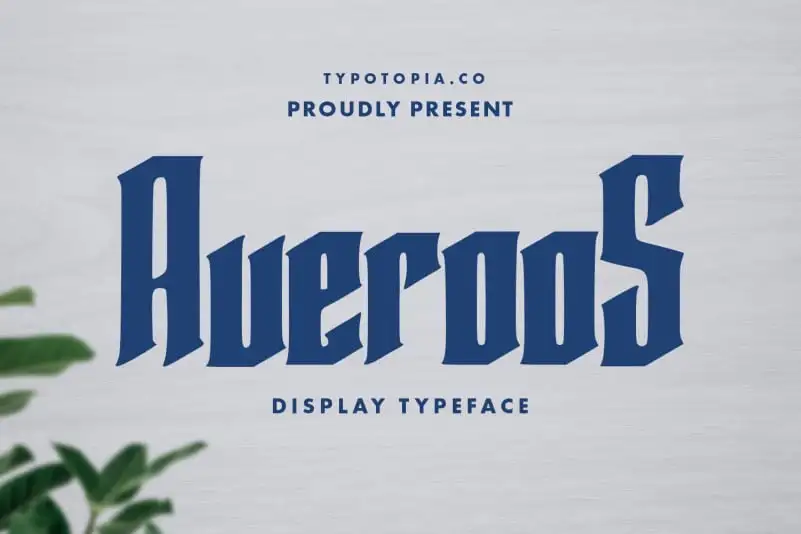
Averoos Display Font – Download Grátis
Introduzimos a Averoos Display Font – uma tipografia de destaque com estilo Semi-Vintage. Este tipo de letra foi projetada para ser aplicada especificamente em logotipos, posters, material de embalagem, revistas, menus, livros, convites, cartas de cumprimento, etiquetas, roupas, marketing, cartões de visitas e outros materiais onde o estilo moderno e vintage combinados são especialmente apropriados. Averoos Display Font é perfeita para quem procura uma fonte que ofereça um toque único e divertido sem comprometer a eficácia e legibilidade esperada em qualquer aplicação visual, sejam elas pequenas ou grandes escala. Ideal tanto para estilos mais conservadores quanto para uma abordagem mais deslumbrante.